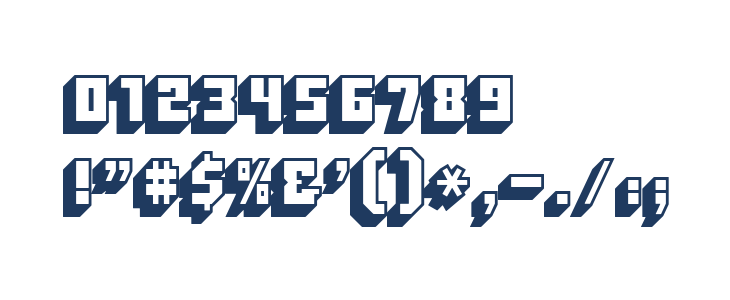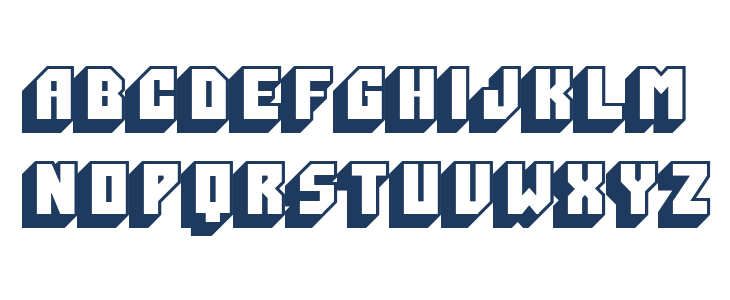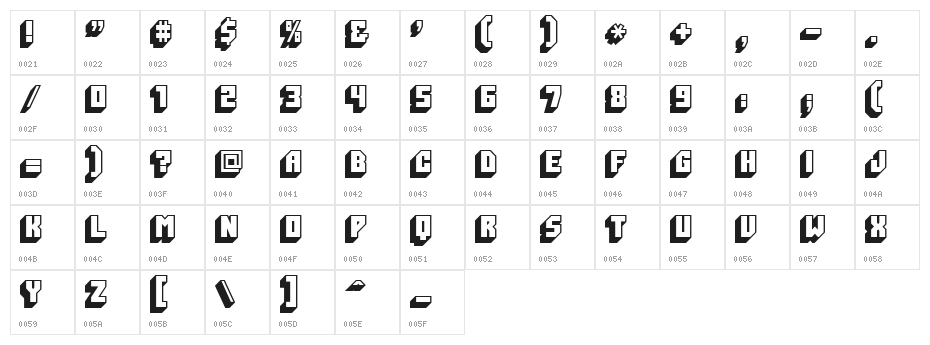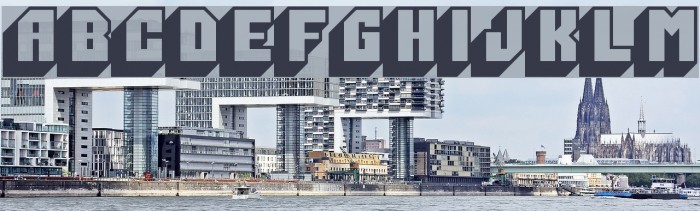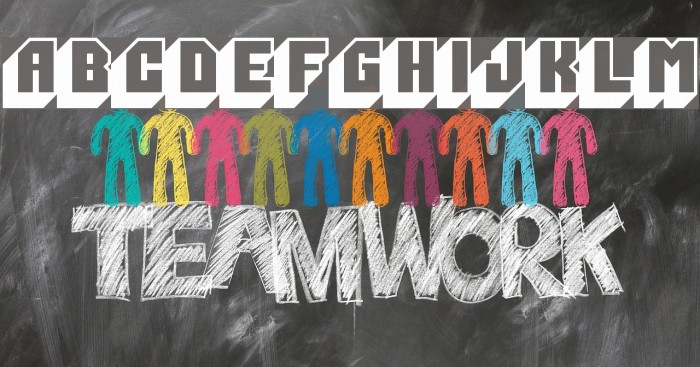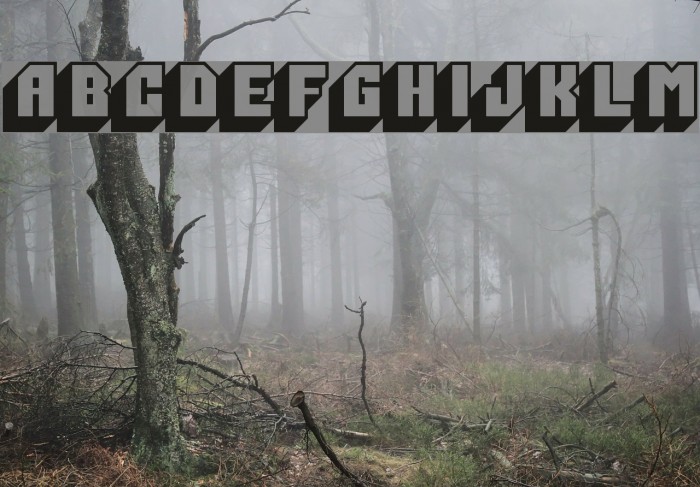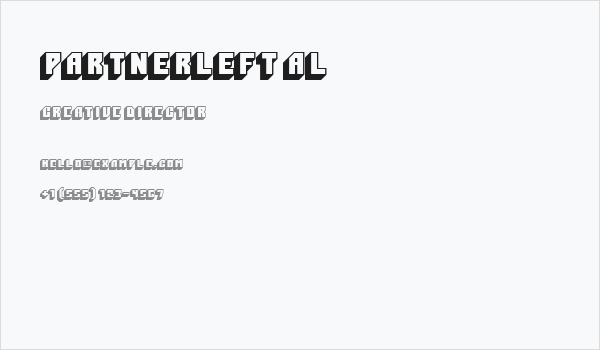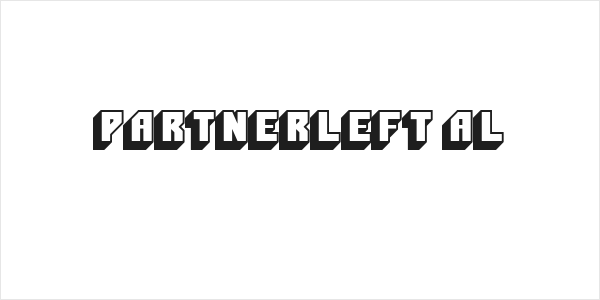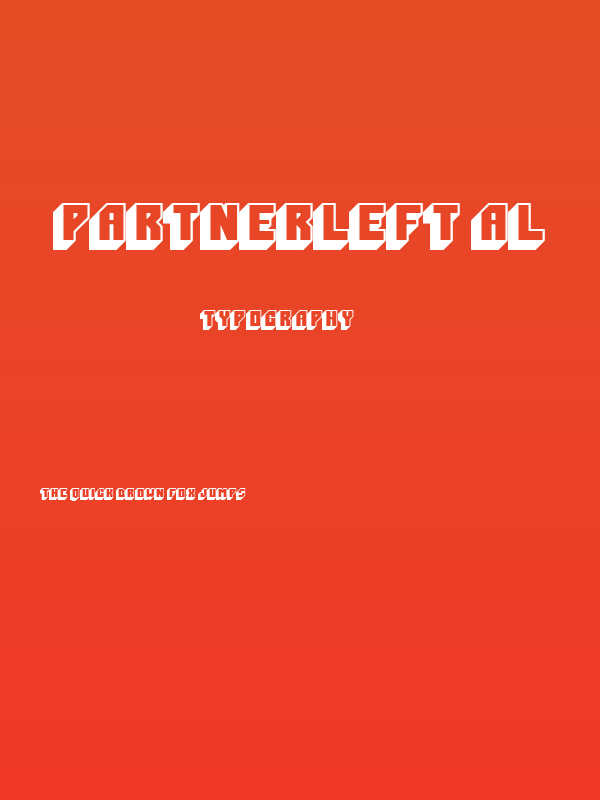
PartnerLeft Al Font
| Progetti proposti | Ideal for poster designs, video game titles, logos, and any project needing a bold, eye-catching typeface. |